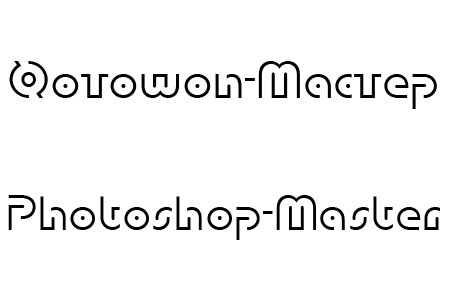
Правда, нестандартный. Я его по телевизору где-то видел
подскажите как называется этот шрифт?
Шрифт очень необычный и это радует. Спасибо
Чёт Покемоны вспомнил
нестандартный, оттого крутой)
Интересный шрифт, именно то что я искал, спасибо огромное!
Оригинальный шрифт. *о* /по тихому тырит/ Спасибо вам! *__*
Прикольный шрифт!
Довольно-таки интересный шрифт и выглядит оригинально,хоть для кого-то может он не читабельный или сразу ктото не прочитал,мой вержикт:
Шрифт для любителя
а по-моему норм читается,и выглядит оригинально,что важнее ;)
Беру. Может пригодится. Хоть и не читабельный:(
Жесть, и не сразу прочтешь )
Как забавно!
Прикольный шрифт. Может пригодится :)
забавно) может пригодиться)